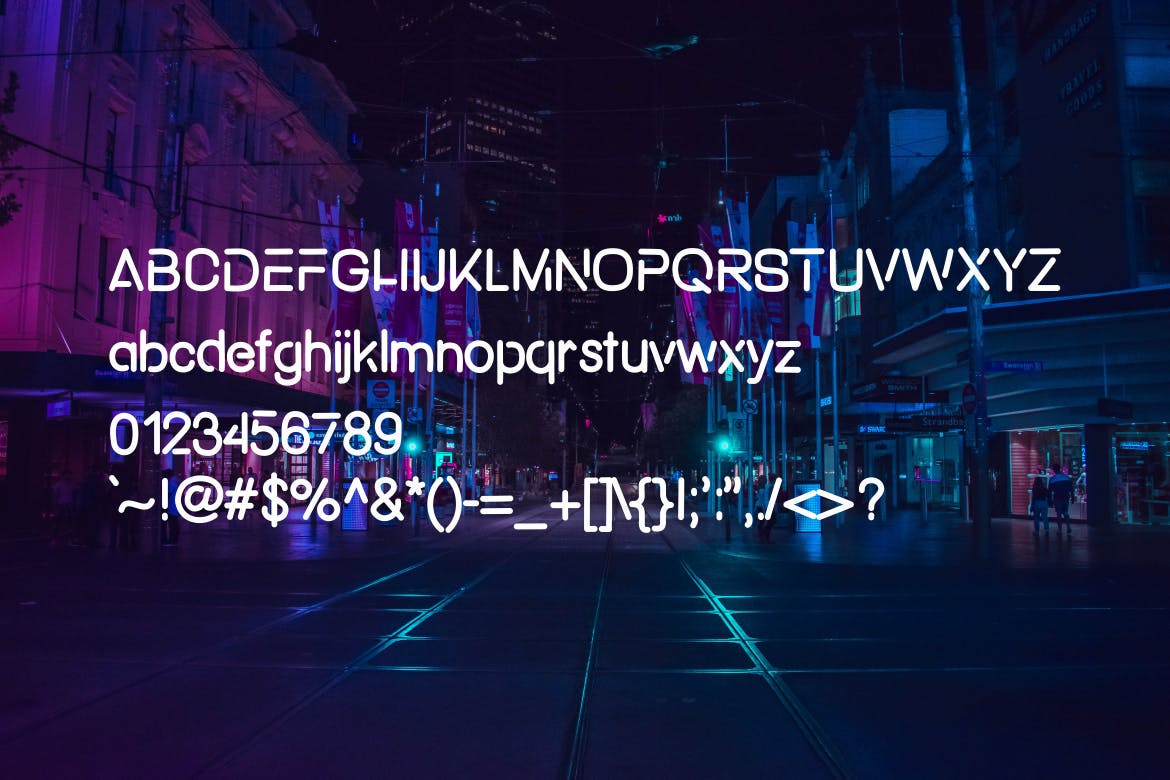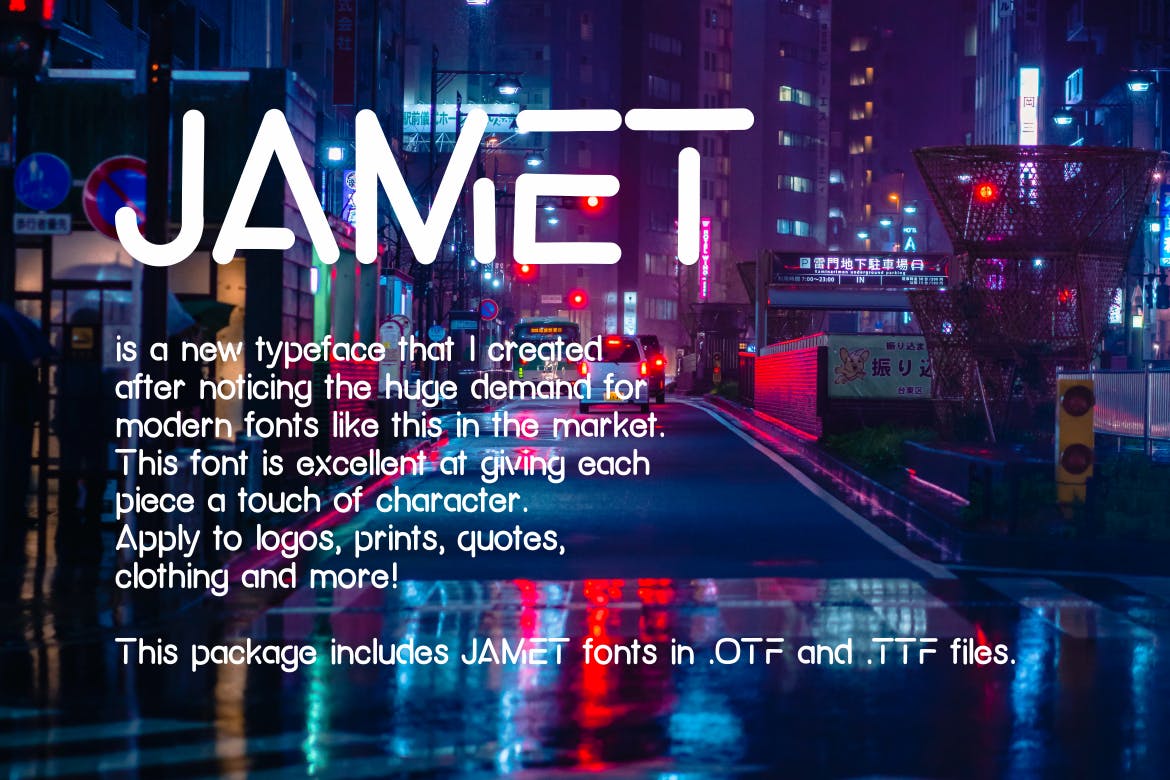
فونت جامت (Jamet) یک نوع تایپفیس جدید است که پس از مشاهده تقاضای بالای بازار برای فونتهای مدرن طراحی کردهام. این فونت به هر اثر طراحی، شخصیت خاصی میبخشد. از آن میتوانید در لوگوها، چاپ، نقل قولها، لباس و موارد دیگر استفاده کنید!